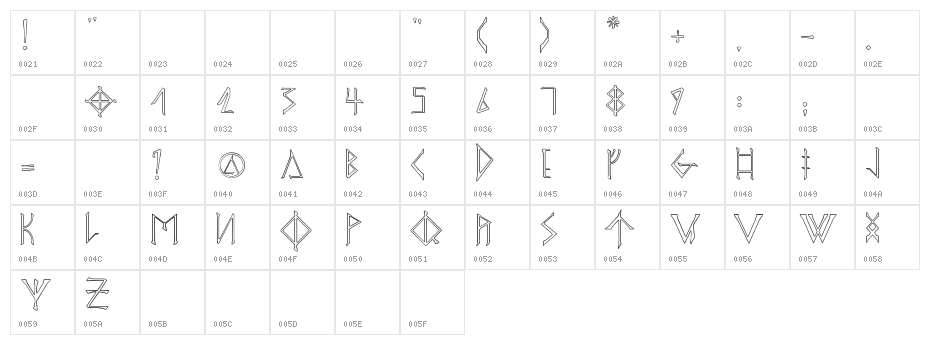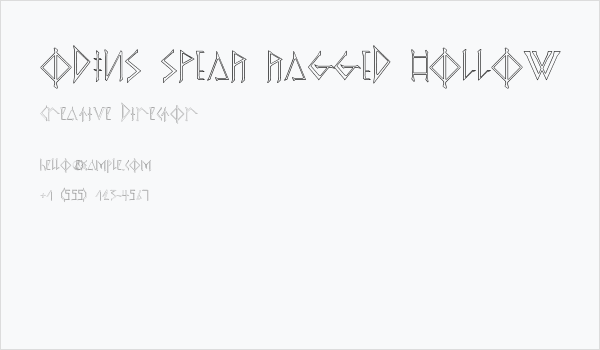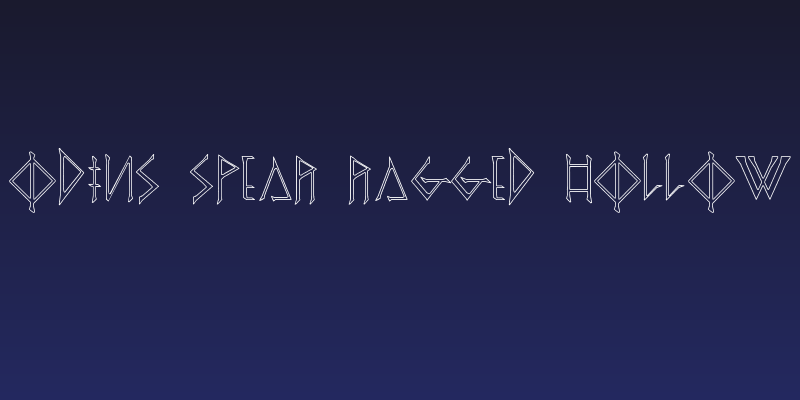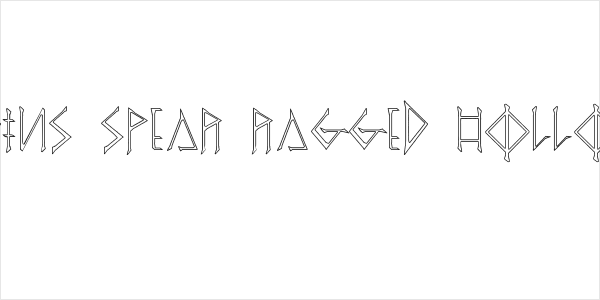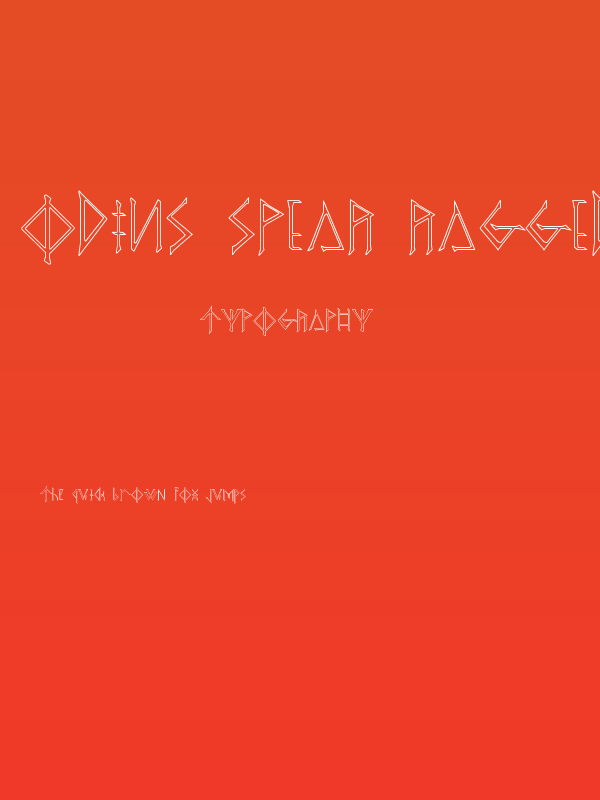
ODINS SPEAR RAGGED HOLLOW Font
✎ Gothic
| Catégories | Gothic |
| Style général | Decorative, Mythical |
| Cas d'utilisation | Logos, Headlines, Themed Events |
| Projets proposés | Ideal for fantasy-themed projects, game titles, book covers, or any design requiring a mythical or historical touch. |